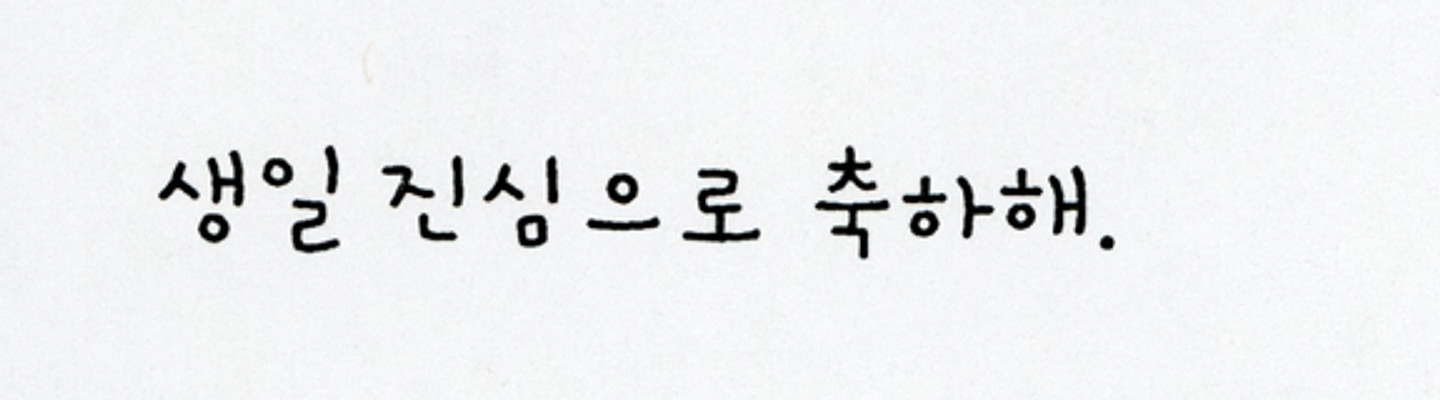
친근하고 귀여운 손글씨 스타일: 정돈된 디지털 폰트보다는 사람이 손으로 직접 쓴 듯한 자연스럽고 따뜻한 느낌을 주는 서체입니다. 둥근 모서리 처리: 거의 모든 획의 끝부분이 각지지 않고 부드럽게 둥글게 처리되어 있어 전체적으로 유하고 다정해 보입니다. 일정한 굵기: 각 글자를 구성하는 획의 굵기가 대부분 일정하며, 굵은 붓펜이나 두꺼운 사인펜으로 쓴 듯한 안정감을 줍니다. 높은 가독성: 손글씨 스타일임에도 불구하고 각 자음과 모음의 형태가 뚜렷하게 구분되어 있어 읽기가 매우 쉽습니다.